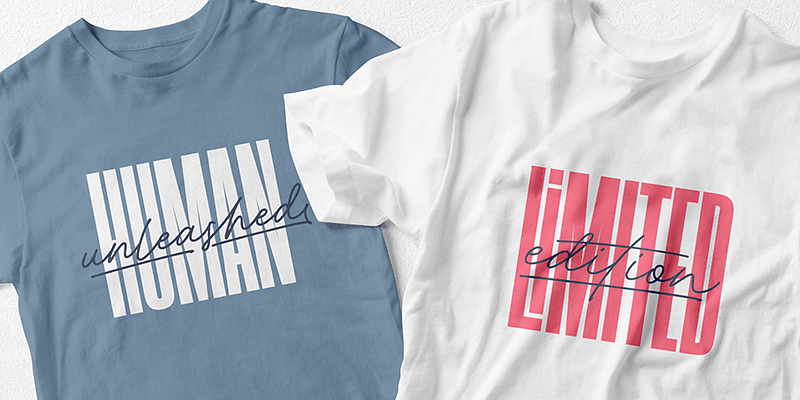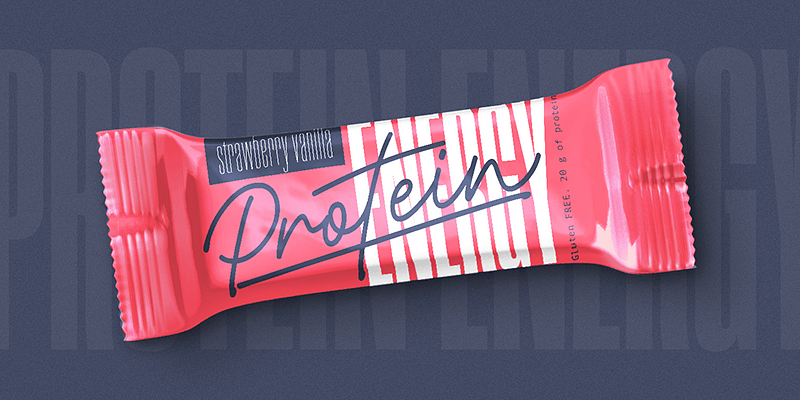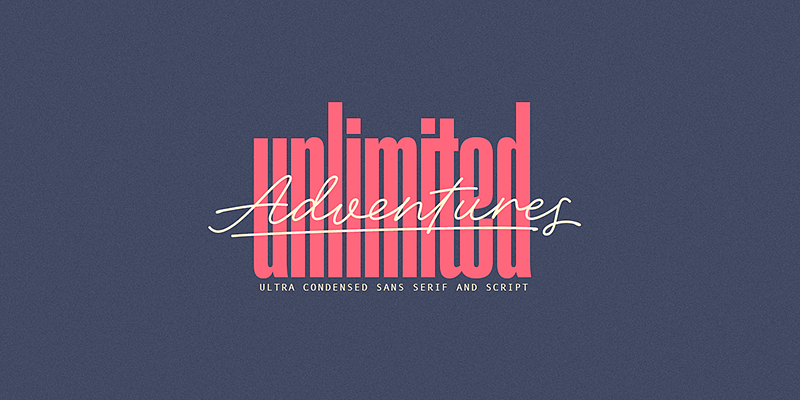
My Creative Land には、Elena Genova の美しく手作りされた書体が揃っています。文字の形の芸術への揺るぎない献身により、書体は日常を超え、デザインに感情、深さ、独自性を伝えます。各ファミリーは丁寧に手作りしており、カリグラフィーやレタリングの美しさから直接インスピレーションを得ていることがよくあります。目の肥えたデザイナーなら、My Creative Land には、自分たちのアイデアを他のフォントよりも際立たせるために、ある種の魅力を注入する準備ができているフォントであることを知っているでしょう。